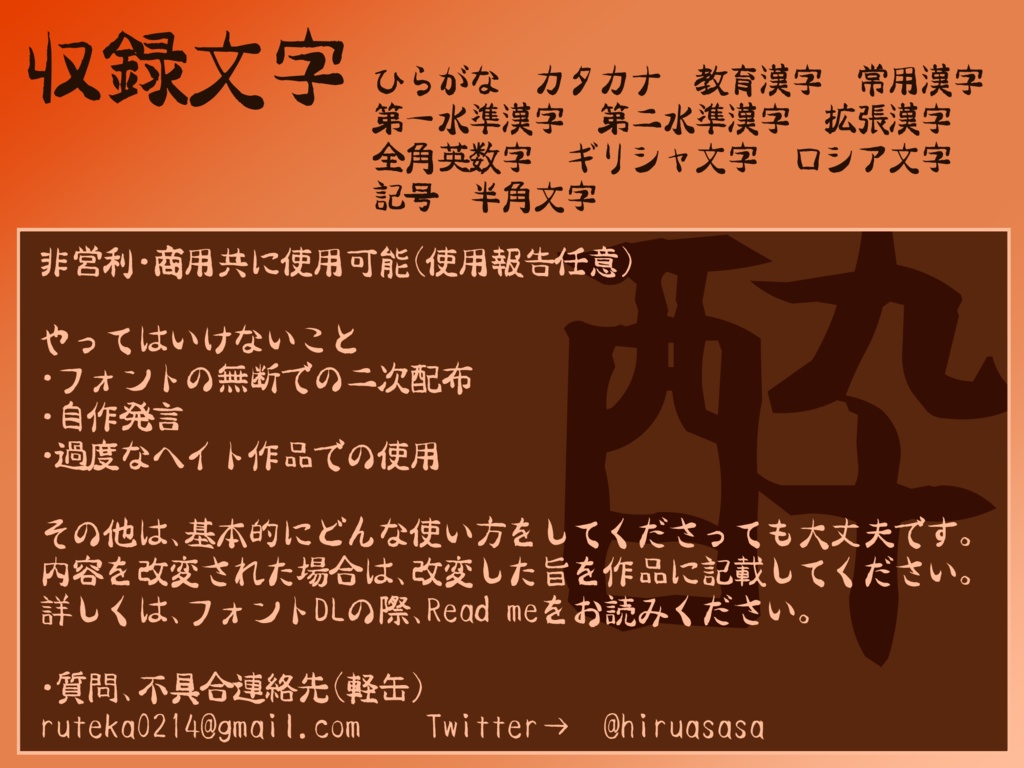
よっぱふでフォント(フリーフォント)
作者の手書き筆文字を少し癖付けしそのまま落とし込んだ、 酔っぱらっているような手書きフリーフォントです。 true type形式です。 収録文字 ・ひらがな ・カタカナ ・教育漢字 ・常用漢字 ・第一水準漢字 ・第二水準漢字 ・拡張漢字 ・全角英数字 ・ギリシャ文字 ・ロシア文字 ・記号 ・半角文字 *禁止事項 ・二次配布 ・自作発言 ・過度なヘイト作品での使用 その他は、基本的にどんな使い方をしてくださっても大丈夫です。 改変された場合は、改変した旨を作品内に記載していただけると嬉しいです。 詳しくはフォルダ内の「Read me」をご覧ください。 そして、お布施版を内容は変わりませんが一応設置してみました。 お気に召しましたらお気持ちを頂けると喜びます。 *よっぱふでフォント(Yoppa-fude font) 作者:軽缶(かるかん) メールアドレス: ruteka0214@gmail.com Twitter: https://twitter.com/hiruasasa 本ファイルは武蔵システム(https://opentype.jp/)の「手書きでフォント」を使って作成しました。